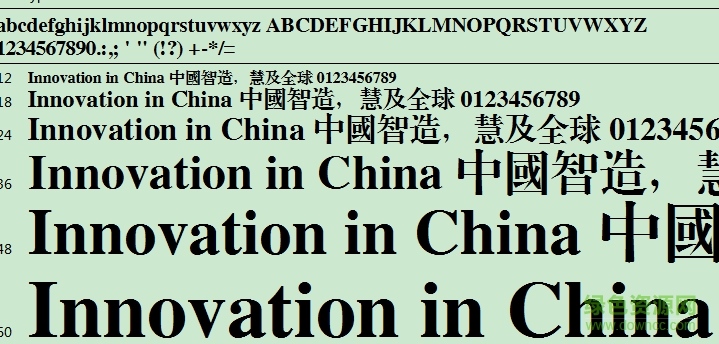
ctbiaosongsf字體也就是創(chuàng)藝繁標宋體,這款字體字體效果端莊、典雅、清秀,整體效果非常出色,這里還有更多好看字體供你下載,歡迎到本站下載體驗!
ctbiaosongsf字體橫細豎粗,筆畫新穎獨特,恰如待放荷苞的點與橫右端的“露滴”相得益彰,互相呼應,增強一份意境。結(jié)構(gòu)上采用扁體,筆畫之間分離,但不影響字形的識別性。整套字體清新雅淡,情趣盎然。此款字體適用于標題、廣告或正文用字。有著極強的應用空間。